Telset.id – Aplikasi font keren dan terbaik cocok sekali digunakan bagi Anda pengguna HP Android yang bosan tampilan font yang gitu-gitu saja. Apabila Anda bingung mau memilih mana aplikasi font terbaik, kami sudah merangkumnya untuk Anda para pembaca setia.
Tim Telset akan membagikan rekomendasi 10 aplikasi font Android keren yang bisa digunakan untuk mengubah bentuk tulisan di smartphone biar gak membosankan.
Nah, berikut ini adalah rekomendasi aplikasi font Android keren dan terbaik yang bisa digunakan untuk mengubah tampilan font di smartphone Anda. Yuk simak daftar lengkapnya di bawah ini.
1. iFont
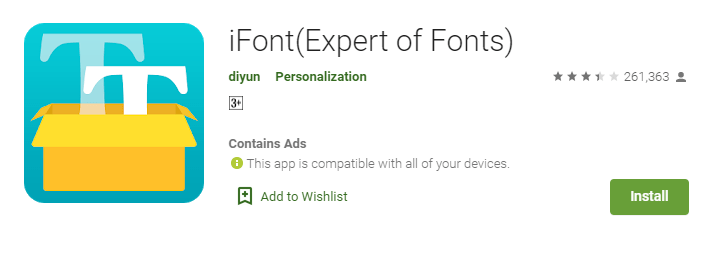
Aplikasi font terbaik untuk Android pertama yang bisa Anda gunakan adalah iFont. Meski namanya iFont, aplikasi ini ditujukan bagi pengguna Android, bukan iOS. iFont menyediakan beragam jenis huruf yang bisa Anda gunakan. Koleksi font yang ada juga diperbarui secara berkala.
Selain bisa mengubah jenis yang digunakan, aplikasi ini juga memungkinkan Anda untuk mengubah warna dan ukuran font. Sehingga bisa Anda sesuaikan dengan selera dan kebutuhan Anda.
2. TextSwag
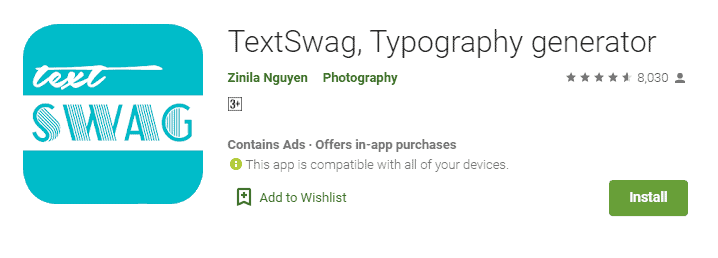
Aplikasi download font Android berikutnya adalah Text Swag. Aplikasi satu ini bisa Anda gunakan untuk mengubah kata-kata yang Anda tulis di Android menjadi desain dan bentuk font yang unik.
TextSwag cocok untuk Anda yang kerap membuat desain-desain berisi kutipan dan gambar. Aplikasi ini membuat Anda bisa memilih banyak jenis font yang lebih bergaya. Setelah desain yang dibuat di aplikasi TextSwag selesai, Anda bisa membagikannya di sosial media pribadi Anda. Asyik, bukan?
3. HiFont
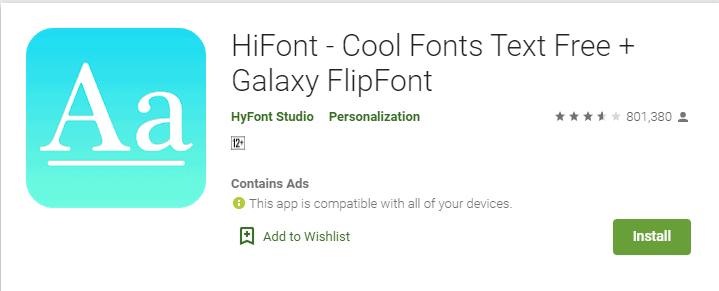
Aplikasi HiFont bisa Anda gunakan untuk mengubah tampilan font di smartphone Android. Koleksi font yang ada lumayan lengkap, sehingga Anda bisa memilih dengan leluasa sesuai dengan selera.
Jika kurang puas dengan font yang disediakan, pengguna juga bisa juga mengimpor font sendiri yang disukai. Bisa dibilang, HiFont menawarkan fitur yang lengkap.
Selain bisa mengubah bentuk font, HiFont memiliki fitur yang memungkinkan Anda untuk mengubah warna font tersebut. Jadi bakal lebih gonjreng lagi tampilannya.
4. FontBoard – Font & Emoji Keyboard
Aplikasi font terbaik untuk Android selanjutnya adalah FontBoard – Font & Emoji Keyboard. Serupa dengan aplikasi lainnya, FontBoard bisa Anda gunakan untuk mengubah gaya font di smartphone Android kesayangan.
Beragam jenis font bagus yang bisa Anda gunakan. Melalui FontBoard, Anda bisa membuat caption di Snapchat atau Instagram dengan style yang berbeda.
Serunya lagi, semua jenis font yang tersedia di FontBoard bisa didapatkan dan digunakan secara cuma-cuma. Pengembang aplikasi ini juga menyebutkan bahwa FontBoard sudah kompatibel dengan beragam aplikasi yang ada di Android.
5. FontChanger
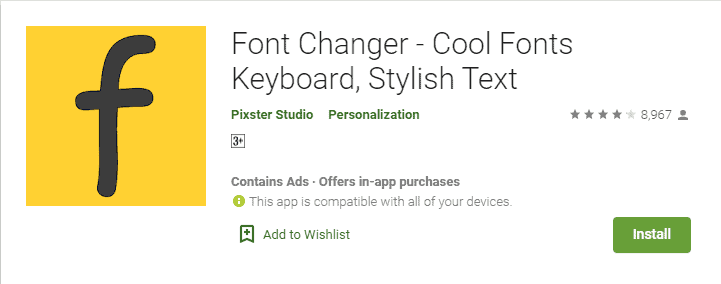
Berikutnya ada Font Changer, yang memungkinkan Anda untuk mengganti font yang ada di smartphone Android dengan mudah. Font Changer akan mengubah bentuk tulisan yang dimasukkan ke dalam aplikasi.
Misalnya, Anda ingin membuat caption atau mengirim teks dengan jenis font yang berbeda, Anda bisa memasukkan teks tersebut ke aplikasi ini terlebih dahulu. Aplikasi ini menyediakan ratusan jenis font yang bisa digunakan. Pastinya bakal membuat tampilan font Anda berbeda dari yang lainnya.
6. Stylish Fonts
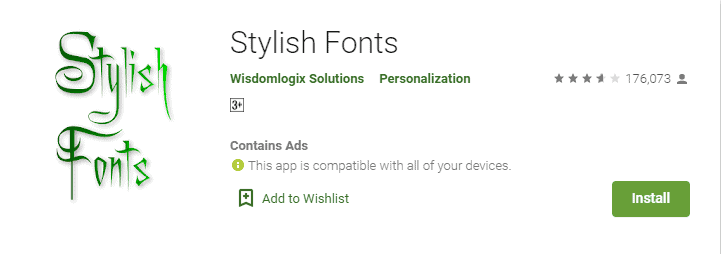
Kemudian, aplikasi font keren dan terbaik untuk Android adalah Stylish Fonts. Sesuai dengan namanya, aplikasi tersebut bisa bikin tampilan font jadi lebih stylish.
Stylish Fonts menyediakan banyak pilihan font yang bisa Anda gunakan. Cocok buat Anda yang merasa bosan dengan tampilan font yang itu-itu saja. Aplikasi ini bisa langsung Anda unduh secara gratis melalui toko aplikasi Google Play Store.
7. FancyKey Keyboard – Cool Fonts
Aplikasi FancyKey Keyboard dapat mengubah tampilan tulisan melalui keyboard yang Anda gunakan. Tersedia beragam jenis font yang bisa dipilih di keyboard.
Selain bisa mengubah font yang Anda ketikkan melalui keyboard, aplikasi font terbaik untuk Android ini bisa mengubah bentuk keyboard, background pada keyboard, dan menghadirkan efek saat mengetik.
8. Fonts for FlipFont 50 Written
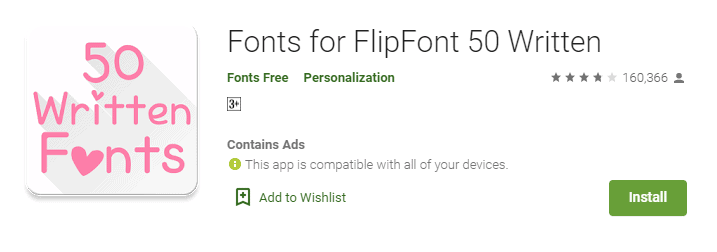
Nah, kalau Anda ingin menggunakan font bergaya ala tulisan tangan, Anda bisa mencoba aplikasi Fonts for FlipFont 50 Writen.
Aplikasi Android ini menyediakan banyak pilihan font keren yang bisa gunakan. Jadi, Anda bisa memilih beberapa varian font yang sesuai dengan selera.
Sedikit kekurangan, aplikasi ini menampilkan cukup banyak iklan yang sedikit mengganggu. Tapi mengingat fungsinya, tentu lebih banyak manfaatnya.
9. Cool Fonts